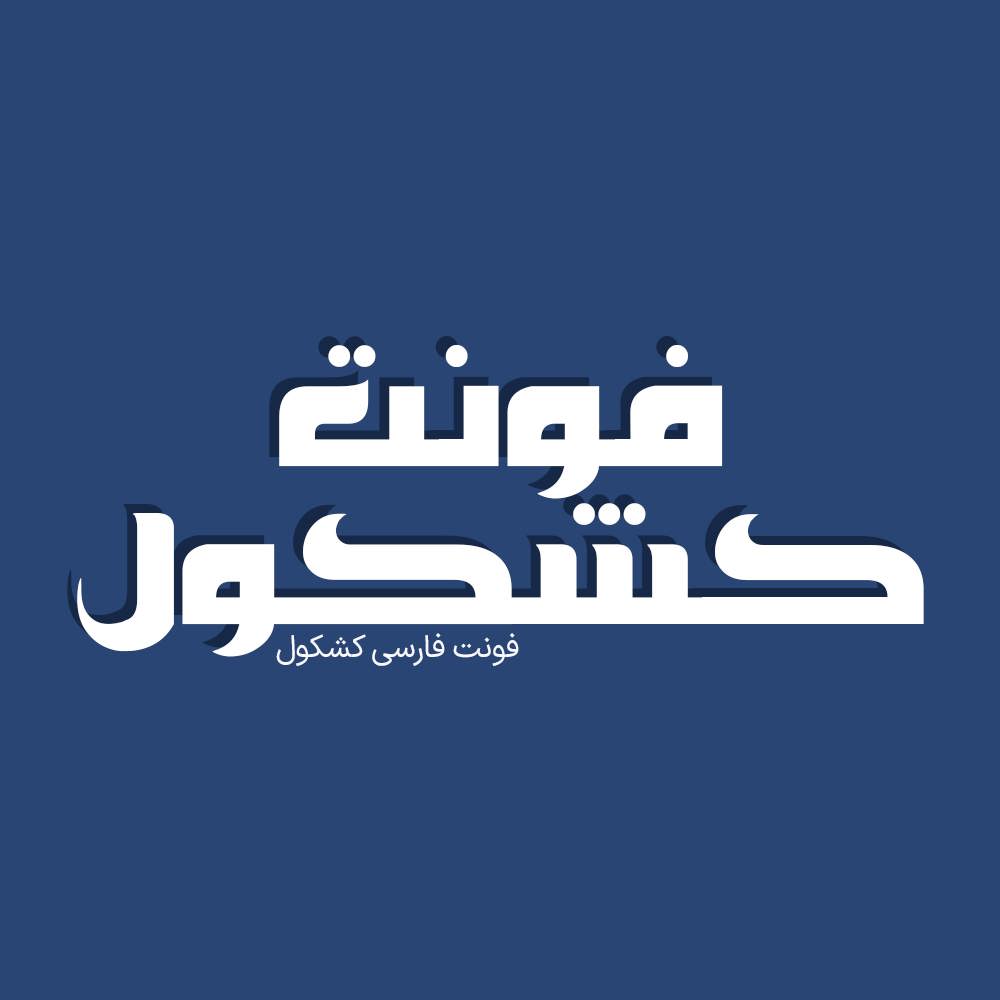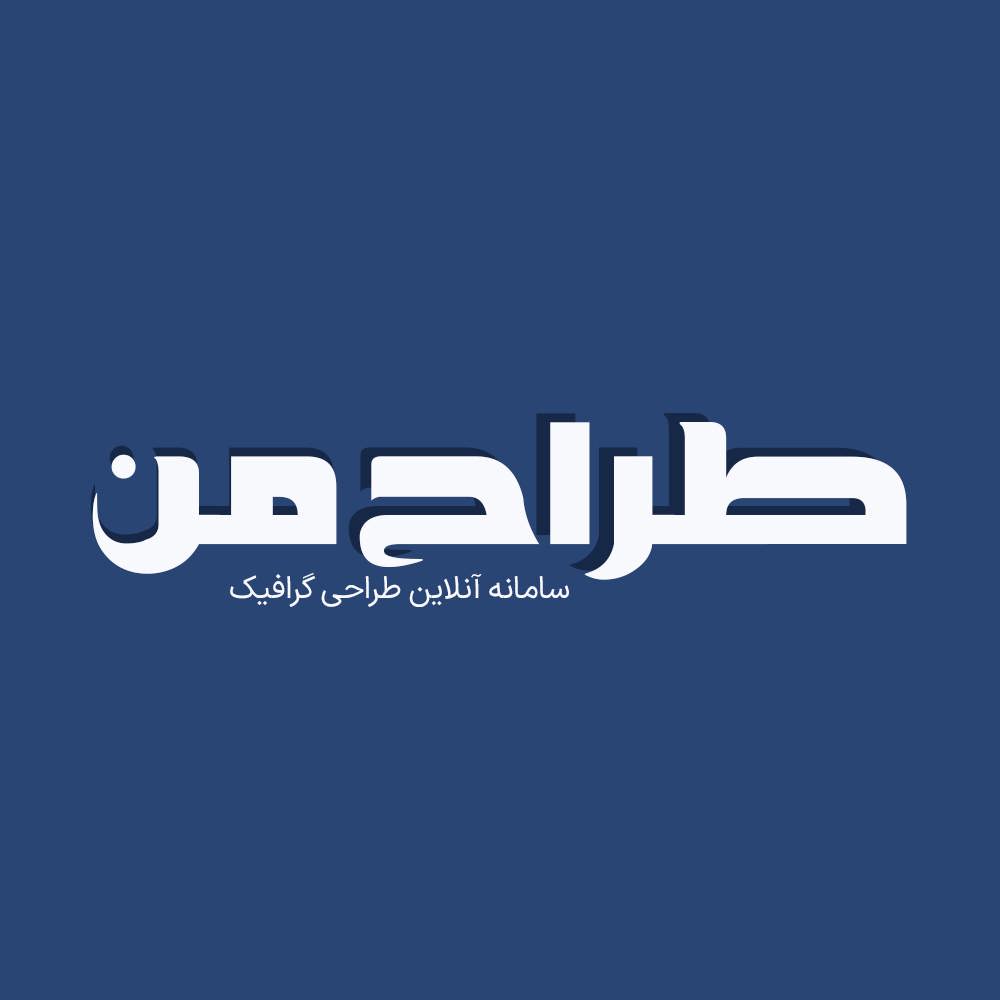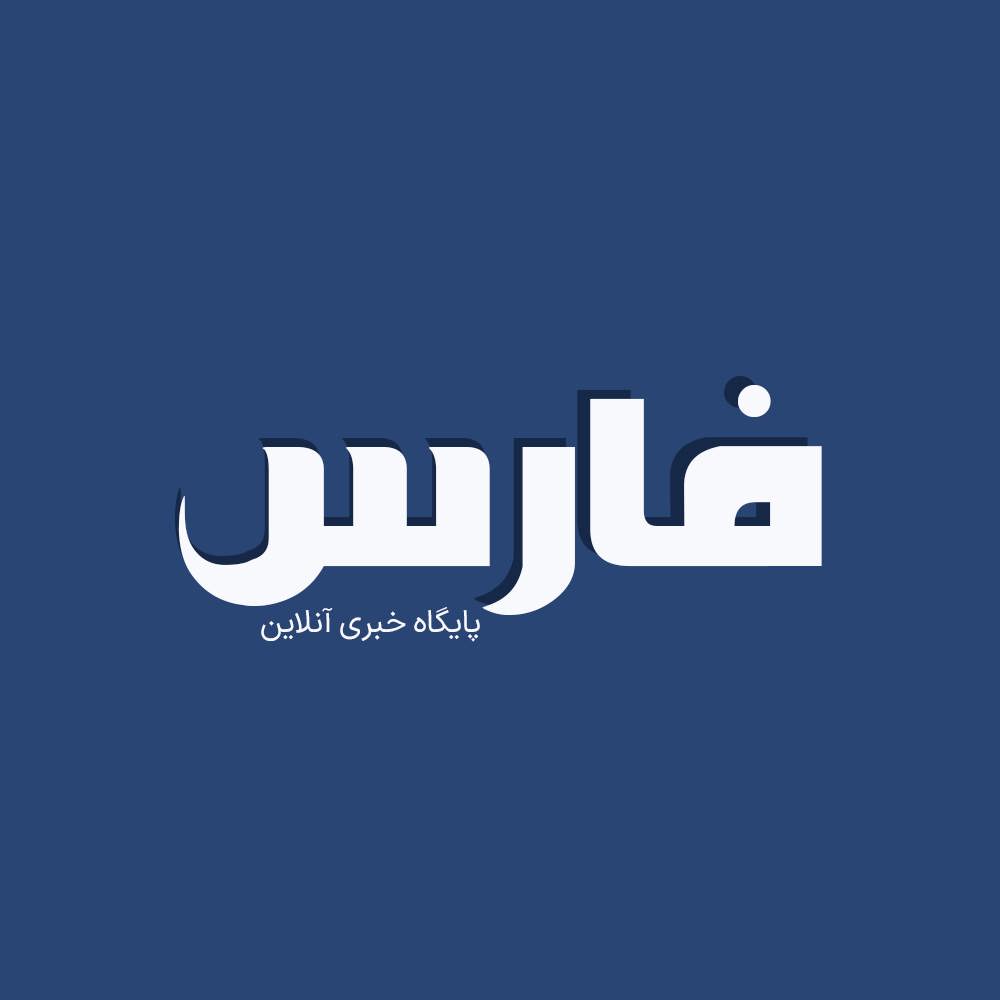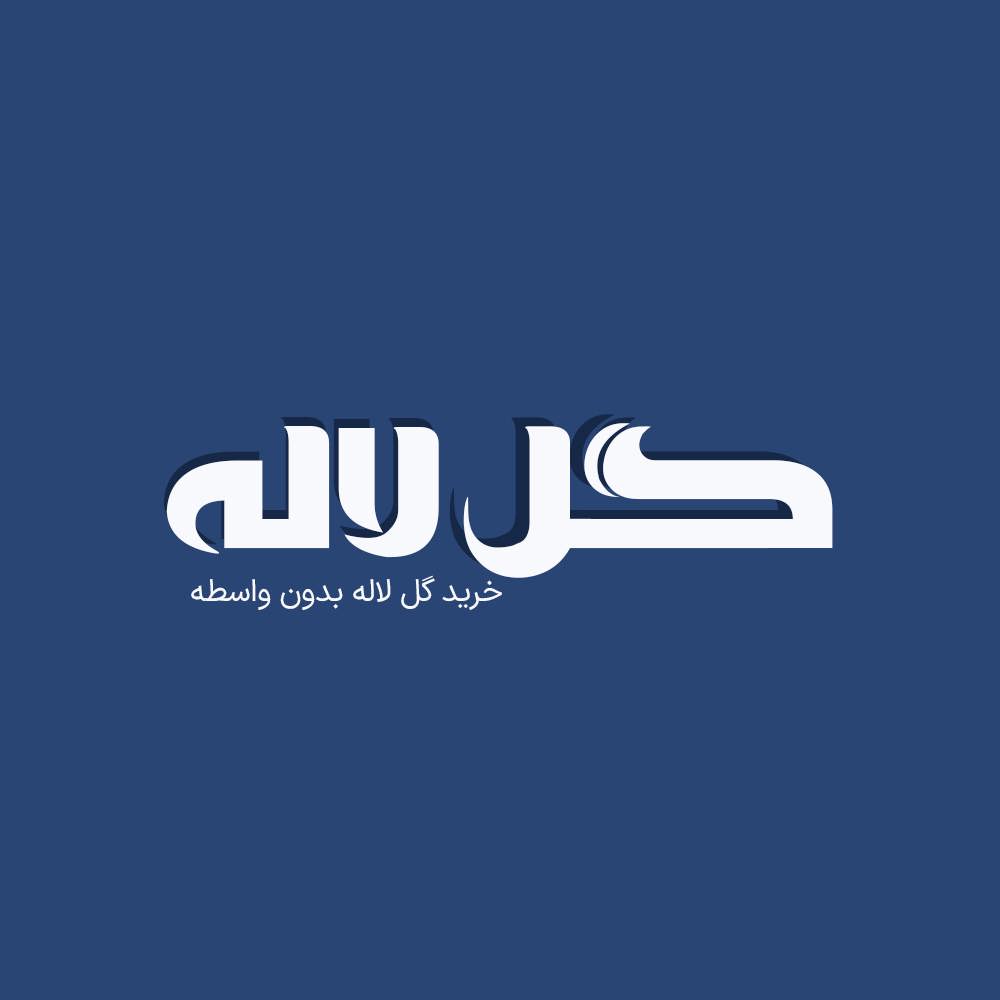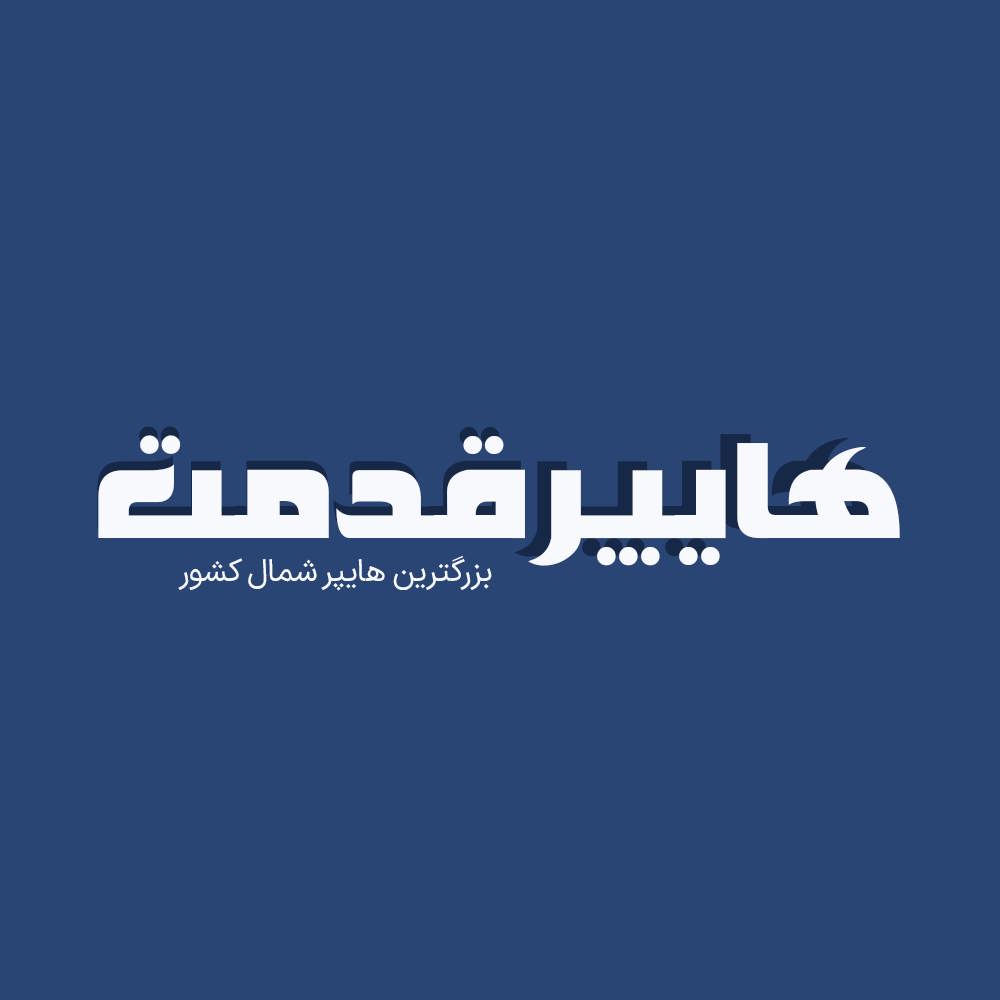
فونت فارسی کشکول یک فونت فارسی بر مبنای حروف هندسی و خاص می باشد که به طراحان گرافیک امکان خلق طرح های زیبا و حرفه ای به سادگی یک تایپ میدهد.
فونت کشکول یک فونت عربی، فارسی سازی و بهینه شده است که برای طراحی انواع امور گرافیکی به خصوص طراحی انواع لوگوتایپ و تایپوگرافی می باشد. از آنجایی که فونت هایی عربی فاقد حروف “گچ پژ” هستند و مشکلاتی در تایپ حروف “ک” و “ی” دارند در فونت کشکول حروف “گچ پژ” و همچنین اعداد فارسی اضافه شده است و اتصالات حروف بازطراحی شده اند تا بتوانید تمامی متن فارسی را به وسیله این فونت تایپ کنید. در ادامه برای شما نمونه تایپ های این محصول حرفه ای رو آماده کردیم که میتونید مشاهده کنید.
پیشنمایش و نمونه تایپ های فونت کشکول